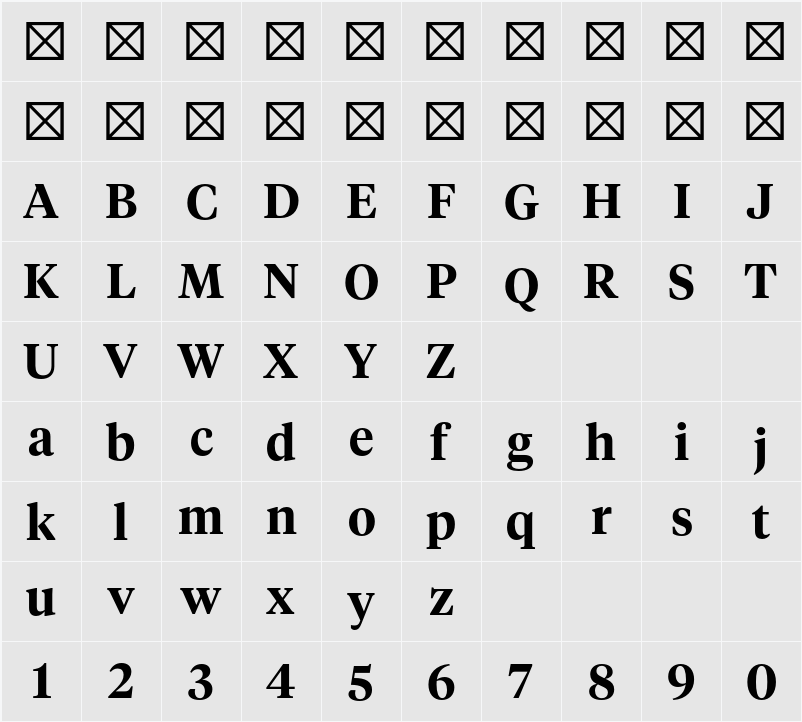
Tiempos Headline Semibold
Tiempos Headline Semibold,这款字体结构工整、笔画清晰,兼顾美观与易读性,适用于标题、正文、海报、包装、LOGO 等多种场景。字形优雅稳定,风格百搭耐看,适配日常排版与创意设计,让文字呈现更舒适、更具质感。Tiempos Headline Semibold一笔一画,皆是细节,以均衡的比例、流畅的线条打造舒适视觉体验,字形端正大气,风格简约现代。无论是商业设计、品牌宣传还是日常排版,都能轻松驾驭,让文字更有格调与力量。Tiempos Headline Semibold字体下载。
• 字体制造商: Klim Type Foundry
• 字体设计师: Kris Sowersby